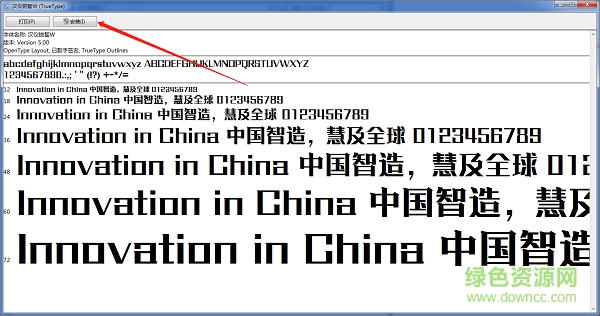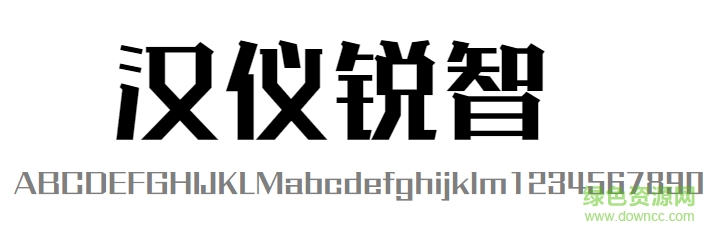
漢儀銳智w字體是一款筆鋒剛硬的含義字體,字體設(shè)計(jì)豐富,融入了黑體的模式,整體展現(xiàn)上加粗,非常實(shí)用日常設(shè)計(jì)叫醒目之處,需要的用戶快來(lái)綠色資源網(wǎng)下載吧!
漢儀銳智W字體是一款非常有個(gè)性的藝術(shù)字體,字體結(jié)構(gòu)醒目,簡(jiǎn)潔大方,非常有特色,能夠適用于藝術(shù)設(shè)計(jì)、包裝印刷、簽名設(shè)計(jì)、圖形設(shè)計(jì)等領(lǐng)域,本站提供了漢儀銳智W字體下載哦!